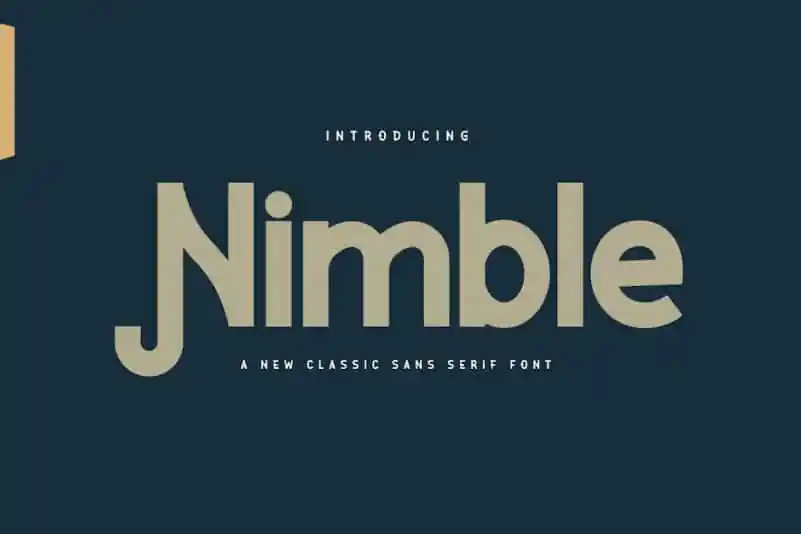
Nimble Sans Serif é uma fonte que se destacou pela sua singularidade única. Introduzida recentemente, Nimble oferece uma mistura intrigante de elegância e formalidade sem deixar de lado um toque amigável e alegre. Suas letras contêm elementos distintos, mas ainda mantém um padrão harmonioso que equilibra modernidade e sofisticação. Além disso, Nimble Sans Serif se destaca pelo seu encantamento nas letras maiúsculas. Possui uma riqueza de personalidades únicas em cada uma delas. Esta característica particular do designer twinletter torna a fonte ainda mais especial, permitindo que você crie nomes e logotipos inovadores e capturantes com apenas um pouco de criatividade.